一、文字设计总述
文字设计意为对文字按视觉设计规律加以整体的精心安排。文字设计是人类生产与实践的产物,是随着人类文明的发展而逐步成熟的。进行文字设计,必须对它的历史和演变有个大概的了解。
世界各国的历史尽管有长有短,文字的形式也不尽相同,但世界文字在历经悠久的历史长河之后,逐步形成代表当今世界文字体系的两大板块结构:代表华夏文化的汉字体系和象征西方文明的拉丁字母文字体系。汉字和拉丁字母文字都是起源于图形符号,各自经过几千年的演化发展,最终形成了各具特色的文字体系。
中国文字 拉丁字母
汉字仍然保留了象形文字图画的感觉,字形外观规整为方形,而在笔画的变化上呈现出无穷含义。每个独立的汉字都有各自的含义,在这一点上和拉丁字母文字截然不同。因而在汉字的文字设计上更重于形意结合。
拉丁字母文字是由26个简单字母组成的完整的语言体系,拉丁字母本身没有含义,必须以字母组合构成词来表述词义。其字母外形各异,富于变化,在字体整体设计上有很好的优势。
二、汉字的历史
中国文字——汉字的产生,有据可查的,是在约公元前14世纪的殷商后期,这时形成了初步的定型文字,即甲骨文。甲骨文既是象形字又是表音字,至今汉字中仍有一些和图画一样的象形文字,十分生动。
象形文字
到了西周后期,汉字发展演变为大篆。大篆的发展结果产生了两个特点:一是线条化,早期粗细不匀的线条变得均匀柔和了,它们随实物画出的线条十分简练生动;二是规范化,字形结构趋向整齐,逐渐离开了图画的原形,奠定了方块字的基础。
后来秦朝丞相李斯对大篆加以去繁就简,改为小篆。小篆除了把大篆的形体简化之外,并把线条化和规范化达到了完善的程度,几乎完全脱离了图画文字,成为整齐和谐、十分美观的基本上是长方形的方块字体。但是小篆也有它自己的根本性缺点,那就是它的线条用笔书写起来是很不方便的,所以几乎在同时也产生了形体向两边撑开成为扁方形的隶书。
大篆 小篆 隶书(张迁碑)
至汉代,隶书发展到了成熟的阶段,汉字的易读性和书写速度都大大提高。隶书之后又演变为章草,而后今草,至唐朝有了抒发书者胸臆,寄情于笔端表现的狂草。随后,糅和了隶书和草书而自成一体的楷书(又称真书)在唐朝开始盛行。我们今天所用的印刷体,即由楷书变化而来。介于楷书与草书之间的是行书,它书写流畅,用笔灵活,据传是汉代刘德升所制,传至今日,仍是我们日常书写所习惯使用的字体。
草书(张旭) 楷书(欧阳询) 行书(王羲之)
到了宋代,随着印刷术的发展,雕版印刷被广泛使用,汉字进一步完善和发展,产生了一种新型书体——宋体印刷字体。印刷术发明后,刻字用的雕刻刀对汉字的形体发生了深刻的影响,产生了一种横细竖粗、醒目易读的印刷字体,后世称为宋体。当时所刻的字体有肥瘦两种,肥的仿颜体、柳体,瘦的仿欧体、虞体。其中颜体和柳体的笔顿高耸,已经略具横细竖粗的一些特征。到了明代隆庆、万历年间,又从宋体演变为笔画横细竖粗、字形方正的明体。原来那时民间流行一种横划很细而竖划特别粗壮、字形扁扁的洪武体,像职官的衔牌、灯笼、告示、私人的地界勒石、祠堂里的神主牌等都采用这种字体。以后,一些刻书工人在模仿洪武体刻书的过程中创造出一种非颜非欧的肤廓体。特别是由于这种字体的笔形横平竖直,雕刻起来的确感到容易,它与篆、隶、真、草四体有所不同,别创一格,读起来清新悦目,因此被日益广泛地使用,成为16世纪以来直到今天非常流行的主要印刷字体,仍称宋体,也叫铅字体。
宋代刻本 制式文字体
在中国文字中,各个历史时期所形成的各种字体,有着各自鲜明的艺术特征。如篆书古朴典雅,隶书静中有动,富有装饰性,草书风驰电掣、结构紧凑,楷书工整秀丽,行书易识好写,实用性强,且风格多样,个性各异。
汉字的演变是从象形的图画到线条的符号和适应毛笔书写的笔画以及便于雕刻的印刷字体,它的演进历史为我们进行中文字体设计提供了丰富的灵感。在文字设计中,如能充分发挥汉字各种字体的特点及风采,运用巧妙,构思独到,定能设计出精美的作品来。
三、拉丁字母文字的历史
拉丁字母起源于图画,它的祖先是复杂的埃及象形字。大约6000年前在古埃及的西奈半岛产生了每个单词有一个图画的象形文字。经过了腓尼基亚的子音字母到希腊的表音字母,这时的文字是从右向左写的,左右倒转的字母也很多。最后罗马字母继承了希腊字母的一个变种,并把它拉近到今天的拉丁字母,从这里开始了拉丁字母历史有现实意义的第一页。
埃及象形文字
腓尼基亚字母
古希腊字母
古罗马字母
当时的腓尼基亚人对祖先的30个符号加以归纳整理,合并为22个简略的形体。后来,腓尼基亚人的22个字母传到了爱琴海岸,被希腊人所利用。公元前1世纪,罗马实行共和时,改变了直线形的希腊字体,采用了拉丁人的风格明快、带夸张圆形的23个字母。最后,古罗马帝国为了控制欧洲,强化语言文字沟通形式趋一,也为了适应欧洲各民族的语言需要,由I派生出J,由V派生出U和W,遂完成了26个拉丁字母,形成了完整的拉丁文字系统。
罗马字母时代最重要的是公元1到2世纪与古罗马建筑同时产生的在凯旋门、胜利柱和出土石碑上的严正典雅、匀称美观和完全成熟了的罗马大写体。文艺复兴时期的艺术家们称赞它是理想的古典形式,并把它作为学习古典大写字母的范体。它的特征是字脚的形状与纪念柱的柱头相似,与柱身十分和谐,字母的宽窄比例适当美观,构成了罗马大写体完美的整体。
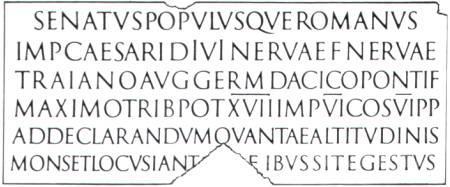
柱体上的罗马字体
在早期的拉丁字母体系中并没有小写字母,公元4世纪--7世纪的安塞尔字体和小安塞尔字体是小写字母形成的过渡字体。公元8世纪,法国卡罗琳王朝时期,为了适应流畅快速的书写需要,产生了卡罗琳小写字体,传说它是查理一世委托英国学者凡·约克在法国进行文字改革整理出来的。它比过去的文字写得快,又便于阅读,在当时的欧洲广为流传使用。它作为当时最美观实用的字体,对欧洲的文字发展起了决定性的影响,形成了自己的黄金时代。
安塞尔字体
卡罗琳小写字体
15世纪是欧洲文化发展极为重要的时期,在这一时期德国人古腾堡发明铅活字印刷术,对拉丁字母形体的发展起了极为重要的影响。原来一些连写的字母被印刷活字解开了,开创了拉丁字母的新风格。同时这一时期正是欧洲文艺复兴时期,技术与文化的发展、繁荣迅速推动了拉丁字母体系的发展与完善,流传下来的罗马大写字体和卡罗琳小写字体通过意大利等国家的修改设计,完美地融合在一起。卡罗琳小写字体经过不断的改进,这时得到了宽和圆的形体,它活泼的线条与罗马大写字体娴静的形体之间的矛盾得到了完满的统一。这一时期是字体风格创造最为繁盛的时期。
18世纪法国大革命和启蒙运动以后,新兴资产阶级提倡希腊古典艺术和文艺复兴艺术,产生了古典主义的艺术风格。工整笔直的线条代替了圆弧形的字脚,法国的这种审美观点影响了整个欧洲。法国最著名的字体是迪多(Firmin Didot)的同名字体,更加强调粗细线条的强烈对比、朴素、冷严但又不失机灵可亲。迪多的这种艺术风格符合了法国大革命的精神,是有现实意义的。在意大利,享有“印刷者之王”和“王之印刷者”称号的波多尼 (Giambattista Bodoni)的同名字体和迪多同样有强烈的粗细线条对比,但在易读性与和谐上达到了更高的造诣,因此今天仍被各国重视和广泛的应用着。它和加拉蒙、卡思龙都是属于拉丁字母中最著名的字体。
迪多体 波多尼体
一套完整的字母体系中,数字和标点符号也是重要的组成部分,阿拉伯数字是11世纪从印度经由阿拉伯传到欧洲的。在早期的希腊、罗马文件中是没有标点符号的,文章中的句子用小点分开,直到15世纪,随着印刷业的发展,标点符号才具有专业化。
四、现代文字设计的发展
文字发展的历史也是文字设计的历史,在文字结构定型以后,文字设计开始以基本字体为依据,采用多样的视觉表现手法来创新文字的形式,以体现不同时期的文化、经济特征。印刷技术的发明和欧洲文艺复兴,极大地推动了文字设计在技术与观念上的改进,人们开始讲究艺术效果与科学技术的结合,出现了一种符合人们视觉规律的数比法则与强调色彩、形态、调子及质感的设计字体。工业革命时期,文字设计在商品销售、文化教育和传播科学技术方面发挥了空前的作用。印刷技术的发展加速了文字设计的多样化,由英国人发明的黑体字在字体的形、比例、量感和装饰上作了新的探索。各种符合时代特征的流行字体大量产生。
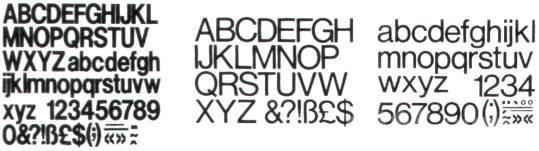
现代主义字体中最为通行的三种字体
现代字体设计理论的确立,则得益于19世纪30年代在英国产生的工艺美术运动和20世纪初具有国际性的新美术运动,它们在艺术和设计领域的革命意义深远。现代建筑、工业设计、图形设计、超现实主义及抽象主义艺术都受到其基本观点和理论的影响。“装饰、结构和功能的整体性”是其强调的设计基本原理。19世纪末20世纪初,源自欧洲的工业革命在各国引发了此起彼伏的的设计运动,推动着平面设计的发展,同时也促使字体设计在很短的二、三十年间发生了许多重大的发展和变化。工艺美术运动和新艺术运动都是当时非常有影响力的艺术运动。它们在设计风格上都十分强调装饰性,而这一时期字体设计的主要形式特点也体现在这个方面。
艾克曼体 莫斯设计的字体标志
20世纪20年代在德国、俄国和荷兰等国家兴起的现代主义设计浪潮提出了新字体设计的口号,其主张是:字体是由功能需求来决定其形式的,字体设计的目的是传播,而传播必须以最简洁、最精练、最有渗透力的形式进行。现代主义也非常强调字体与几何装饰要素的组合编排,从包豪斯到俄国的构成主义设计作品都运用了各种几何图形与字体组合的方法。
各种字体组成的图形
20世纪50年代到60年代,现代主义在全世界产生了重大的影响,以国际字体为基础字体的设计更加精致细腻。随着照像排版技术的发展,进一步使字体的组合结构产生新的格局。60年代中期以后,世界文化艺术思潮发生了巨大的变化,新的设计流派层出不穷。他们的一个共同特点是反对现代主义设计过分单一的风格,力图寻找新的设计表现语言和方式。在字体设计方面许多设计家运用了新的技术和方法,在设计风格上出现了多元化的状况。
我国的文字设计源远流长。有学者认为,它的产生可推溯到商代及周初青铜器铭文中的图形文字,至今已有3500多年的历史。其间经历了春秋战国以虫鸟书为代表的金文字体、秦汉及其后的篆书字体、宋元明清的宋体印版字体及二十世纪的现代字体设计等几个发展阶段。
民间鸟虫书 鸟虫文
汉字的构成形式决定了它是一种有巨大生命力和感染力的设计元素,有着其他设计元素、设计方式所不可替代的效应,具有强大的说服力与感染力。在现代迅猛发展的社会文化形态、经济活动方式、科学技术条件、大众传播媒介的推动下,现代汉字艺术设计从世界其他国家吸取精华,并将之融合到强烈的民族个性之中,凭借其独特的表情获得强烈的视觉感染力。作为高度符号、色彩的视觉元素,汉字越来越成为一种有效的信息传达手段。
新的文字设计发展潮流中有几种引人注目的倾向。一是对手工艺时代字体设计和制作风格的回归,如字体的边缘处理得很不光滑,字与字之间也排列得高低不一,然后加以放大,使字体表现出一种特定的韵味。其次是对各种历史上曾经流行过的设计风格的改造。这种倾向是从一些古典字体中吸取优美的部分加以夸张或变化,在符合实用的基础上,表现独特的形式美。如一些设计家将歌德体与新艺术风格的字体简化,强化其视觉表现力度,并使之具有一些现代感。还有的将强调曲线的早期新艺术运动的字体加以变化,使其具有光效应艺术的一些视觉效果。另外产生了不少追求新颖的新字体,普遍现象是字距越来越窄,甚至连成一体或重叠,字形本身变形也很大,有些还打破了书写常规,创造了新的连字结构,有的单纯追求形式,倾向于抽象绘画的风格。
以歌德体为基础的新字体
20世纪80年代以来,电脑技术不断完善,在设计领域逐步成为主要的表现与制作工具。在这个背景下,字体设计出现了许多新的表现形式。利用电脑的各种图形处理功能,将字体的边缘、肌理进行种种处理,使之产生一些全新的视觉效果。最后是运用各种方法,将字体进行组合,使字体在图形化方面走上了新的途径。